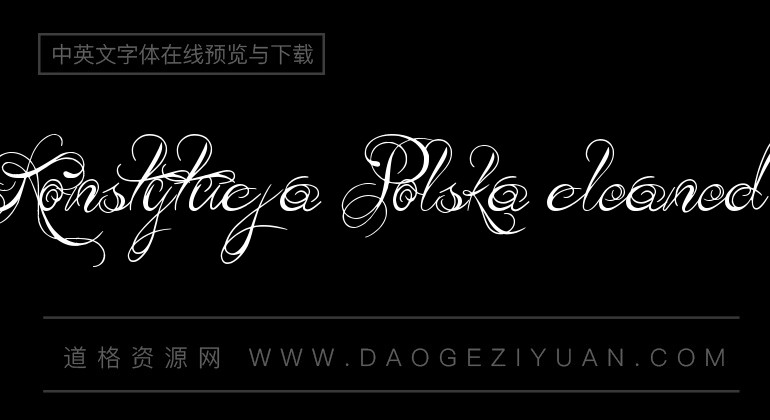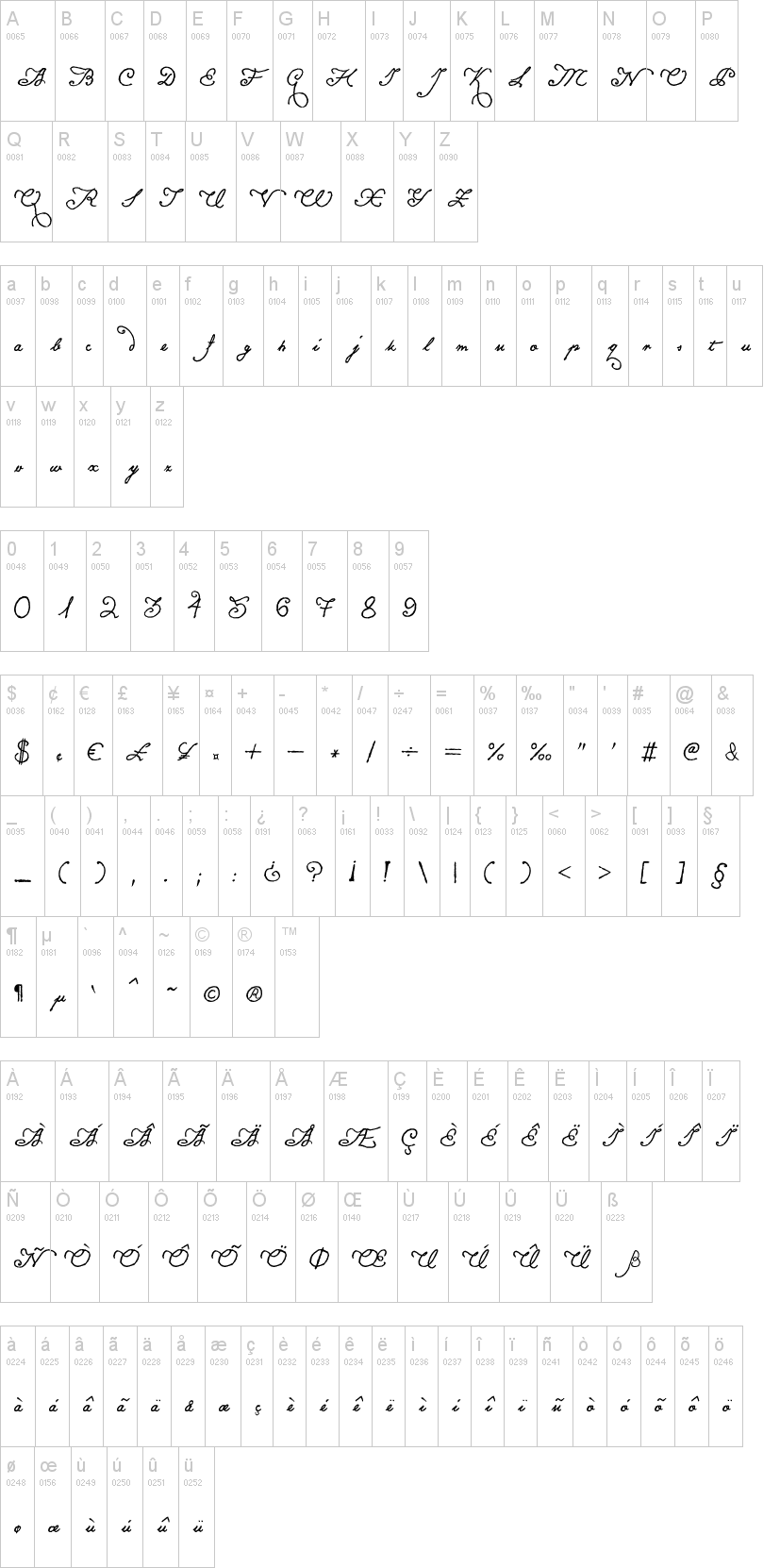
Konstytucja Polska cleaned
Konstytucja Polska 是波兰宪法,于1997年7月2日颁布,是波兰独立后的第一部宪法。它的目的是建立一个民主、自由、法治的社会,保障公民的基本权利和自由,并确保波兰的主权和独立。它共分为16章,共包含235条条款,对波兰的政治、经济、文化、社会等各个方面都有明确规定。Konstytucja Polska字体是一种简洁、优雅的字体,比较细腻,有一定的秩序感,可以更好的表达文字的精神内涵。
Konstytucja Polska cleaned是一款非常不错的手写艺术字体,具有很好的视觉感,适合于文化类的宣传设计、商业类品牌的广告和产品包装设计以及个性化文字排版等较多场景。